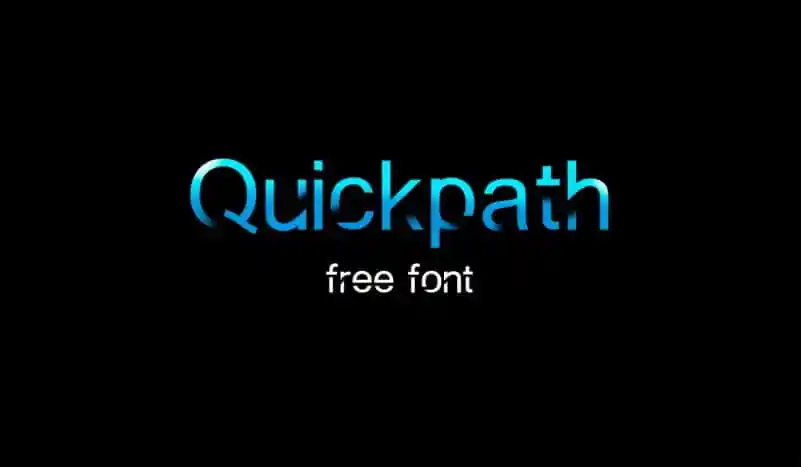
A Quickpath Display Font é uma tipografia de exibição moderna e casual que traz um sabor militar para designs tanto formais quanto informais. Com suas letras bem arranjadas e elegantes, essa fonte se destaca em qualquer aplicação gráfica. É a nova fonte de displays da Piero Unisono, conhecida por seus cortes leves e limpos que proporcionam um toque único para criação de logotipos, identidade visual, embalagens, rótulos e muito mais. Esta fonte é perfeita para quem busca uma mistura atraente entre simplicidade e sofisticação. Seja você criador de arte digital ou designer gráfico tradicional, o Quickpath Display Font trará originalidade aos seus projetos sem sacrificar facilidade de uso. Descubra sua versão gratuita e descubra por si mesmo como essa fonte pode revolucionar suas criações!